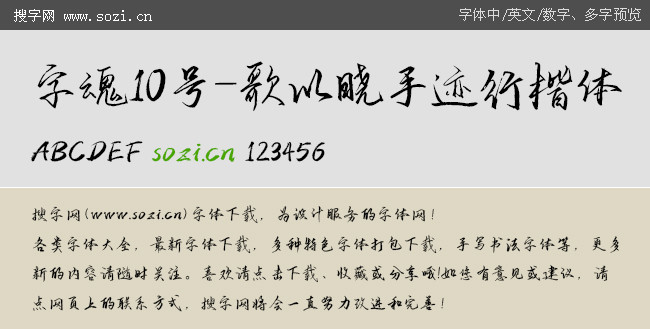
字魂10號-歌以曉手跡行楷體
搜字網(wǎng)提供一款字魂10號-歌以曉手跡行楷體中文字體下載,該字體是一款毛筆書法手寫字體,該字體包含6763個中文、字母、 符號和數(shù)字,具有女性、優(yōu)雅、浪漫、中國風 的風格,可以滿足您設計上的各種需求,該字體主要用于店鋪、活動、美食餐飲、健康養(yǎng)生 等場景。